10 Fuentes Google Fonts más populares y cómo usarlas
Si estás planeando usar Google Fonts en tu sitio web, esta guía te ayudará no solo a elegir la fuente adecuada para tu diseño, sino también a aprender cómo instalarlas correctamente.
En este artículo, hemos seleccionado las Google Fonts más creativas que ofrecen la mejor experiencia de lectura, junto con consejos para usarlas eficientemente.
Recuerda: No elijas una fuente solo por su popularidad. Considera siempre a tus usuarios, tu marca y tu público objetivo.
¿Por qué usar Google Fonts?
4 consejos para usar Google Fonts efectivamente
- Usa máximo 2 fuentes
- Una para títulos y otra para contenido
- Usar muchas fuentes puede afectar la experiencia del usuario y ralentizar tu sitio
- Limita los pesos de fuente
- Usa solo 2-3 pesos (normal, negrita y cursiva) para mejor rendimiento
- Considera el tamaño del texto
- 16pt-24pt es ideal para contenido web
- Algunas fuentes son mejores para títulos, otras para contenido
- Soporte multilingüe
- Elige fuentes que soporten los idiomas de tu audiencia objetivo
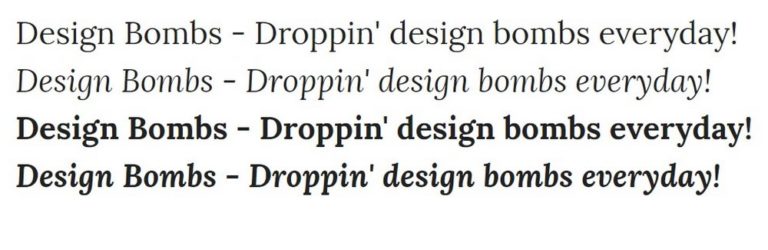
Cómo combinar fuentes (Font Pairing)
En Google Fonts, puedes seleccionar fuentes haciendo clic en el botón (+) junto a cada una. El sistema sugerirá automáticamente combinaciones que funcionan bien juntas.
También puedes usar herramientas como FontPair y Fontjoy para encontrar combinaciones perfectas fácilmente.
Las Google Fonts más populares para sitios web
- Roboto
- Tipo: Sans-Serif
- Ideal para: Contenido
- Usada en más de 26 millones de sitios
- Montserrat
- Tipo: Sans-Serif
- Ideal para: Contenido y títulos
- Playfair Display
- Tipo: Serif
- Ideal para: Títulos
- Lora
- Tipo: Serif
- Ideal para: Noticias y sitios corporativos
- Karla
- Tipo: Sans-Serif
- Ideal para: Contenido
- Merriweather
- Tipo: Serif
- Ideal para: Contenido y títulos
- Ubuntu
- Tipo: Sans-Serif
- Ideal para: Títulos
- Rubik
- Tipo: Sans-Serif
- Ideal para: Títulos
- Source Sans Pro
- Tipo: Sans-Serif
- Ideal para: Contenido
- Archivo
- Tipo: Sans-Serif
- Ideal para: Títulos